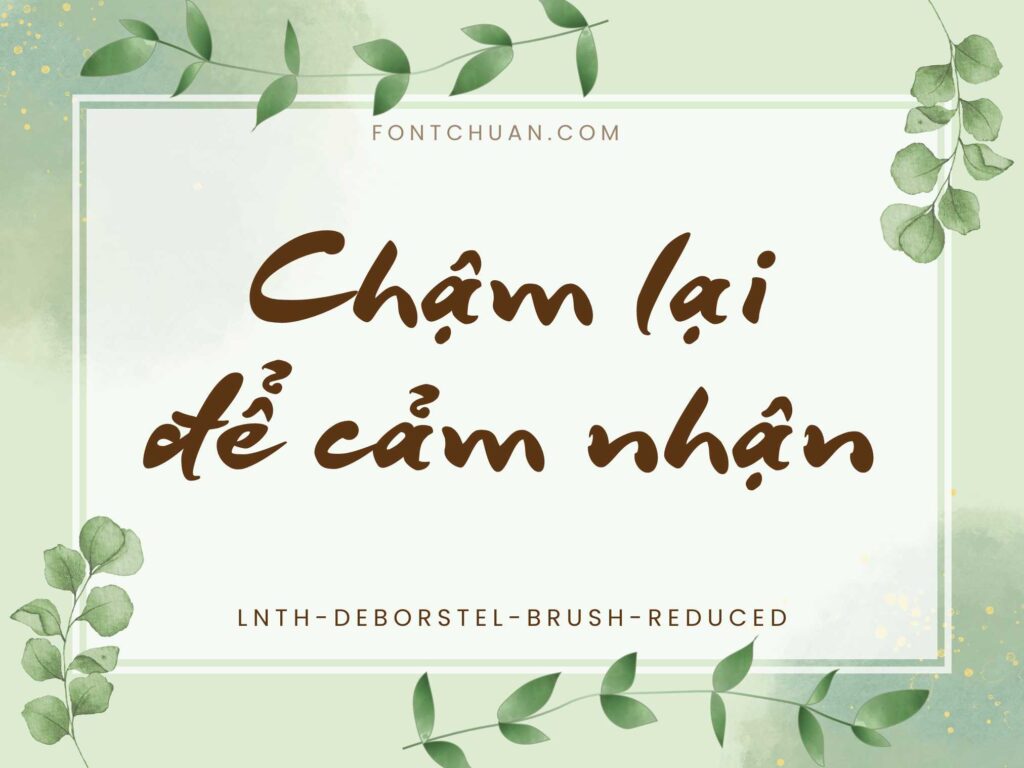
Font LNTH Deborstel Brush Việt Hóa
DeBorstel là một phông chữ viết tay mang phong cách cọ vẽ mạnh mẽ và nghệ thuật. Các đường nét mô phỏng nét cọ tự nhiên, tạo nên sự phóng khoáng và đầy năng lượng cho các thiết kế. Nhờ được Việt hóa bởi LNTH, DeBorstel hỗ trợ đầy đủ các ký tự tiếng Việt, giúp người dùng dễ dàng áp dụng trong các dự án đa ngôn ngữ. Phông chữ này đã được sưu tầm và đăng tải bởi thành viên của Font Chuẩn nhằm đáp ứng nhu cầu đa dạng của cộng đồng thiết kế.
Về đặc điểm thiết kế, DeBorstel sở hữu các ký tự được thiết kế tỉ mỉ với độ dày không đồng đều, mang lại cảm giác chân thực và sống động. Phông chữ này đặc biệt phù hợp cho các dự án như thiết kế poster, bìa sách, logo và các ấn phẩm quảng cáo, nơi cần sự nổi bật và mạnh mẽ. Ngoài ra, DeBorstel cũng thích hợp cho các sự kiện như lễ hội, sinh nhật, Halloween và Trung thu, mang lại không khí sôi động và nghệ thuật. Trong lĩnh vực ngành nghề, phông chữ này được ứng dụng rộng rãi trong quảng cáo, thiết kế thiệp cưới, giáo dục và công nghệ, góp phần tạo nên sự độc đáo và thu hút cho các sản phẩm và thương hiệu.
Tác giả: Mack Trinh Và Harry Dinh
Việt hóa: Mack Trinh Và Harry Dinh